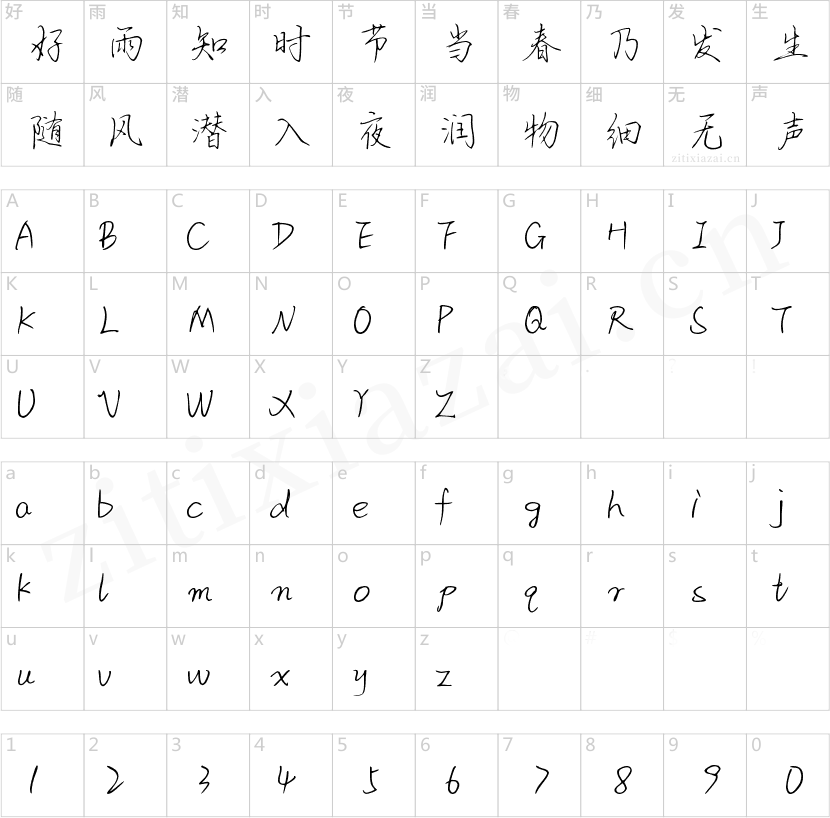
Aa十二时辰
Aa十二时辰字体
Aa十二时辰是一款非常具有艺术性的字体,它的设计灵感来源于对古典艺术的研究,同时又融入了现代字体设计的元素。字形优美,笔画粗细变化自然,给人以大气、典雅的感觉。Aa十二时辰是一款既传统又现代的字体,它的设计充满艺术感,美观大方,实用性也非常强。无论是对于设计师还是对于普通读者来说,都是一种非常不错的字体选择。Aa十二时辰适合用于具有艺术感的场合,比如海报、宣传单张、书籍封面等。由于其字形流畅且具有动态感,也适合用于大量的文本排版,如报纸、杂志等。